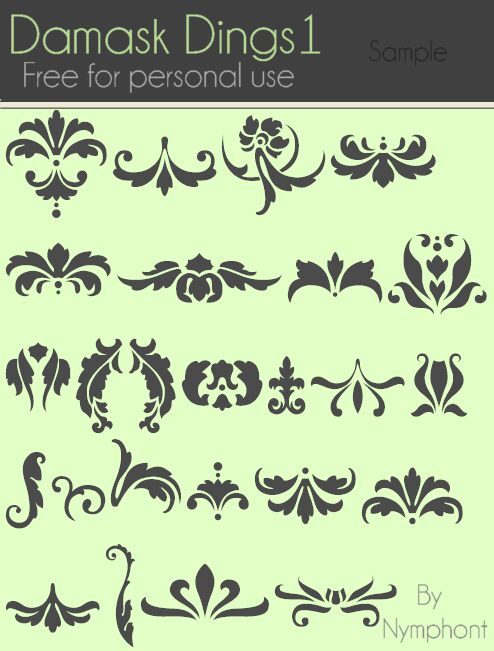
Damask Dings 1 von Lauren Thompson (Nymphont) ist eine kostenlose Dingbat-Schrift mit Damast-Ornamenten, die auf geschwungenen botanischen Formen und eleganten, symmetrischen Schnörkeln basiert. Das Set kombiniert formale Wappenmotive mit kleineren Fleur-de-Lis-Elementen und verspielten Akzenten, was für einen altmodischen, dekorativen Rhythmus ohne überladene Details sorgt.
Die ausgewogenen Silhouetten verleihen Einladungen und Verpackungsdesigns eine raffinierte, heraldische Note. Darüber hinaus ist die kostenlose Schrift ideal, um Speisekarten zu rahmen, Buchcover aufzuwerten oder die Identität von Boutique-Marken zu prägen. Nutzen Sie die Ornamente als Trennelemente, Eckdetails oder als zentrales Emblem in Veranstaltungsprogrammen, wo ihre sich wiederholenden Kurven für ein stimmiges Gesamtbild sorgen.
A set of dingbats inspired by damask prints